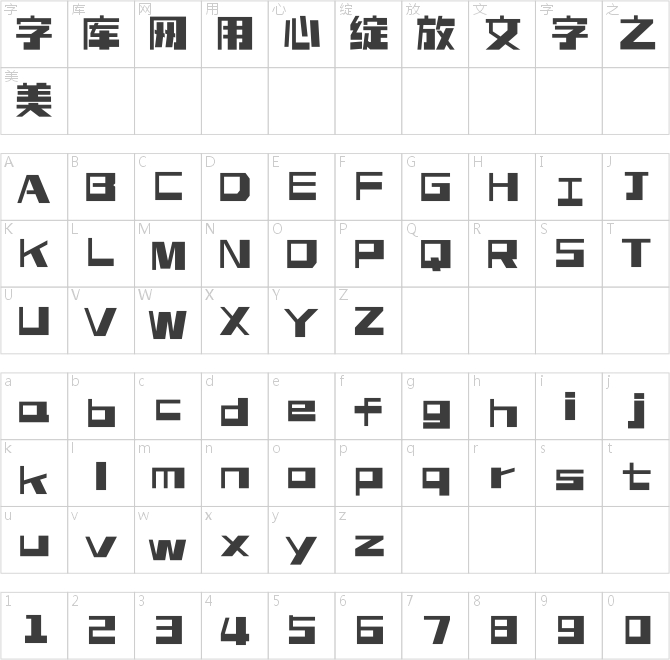
造字工房漢方體,字形設(shè)計(jì)中宮寬大,筆畫(huà)左細(xì)右粗,搭配巧妙,疏密得宜,留白均勻。風(fēng)格穩(wěn)重有力、工整硬朗,結(jié)構(gòu)醒目有力,引人注目,富有時(shí)代感,迎合了現(xiàn)代的審美觀。它適合用于標(biāo)題、廣告語(yǔ)、時(shí)尚刊物、名稱等主信息文字的設(shè)計(jì)。本字體為簡(jiǎn)體字庫(kù),采用OpenType/CID格式,Adobe-GB1-5編碼。基于中華人民共和國(guó)GB2312-80字符集標(biāo)準(zhǔn),另按需添加101個(gè)漢字。共收容字?jǐn)?shù)6864CJK漢字,ASCII常用字符100個(gè)。
造字工房漢方體字體字庫(kù)是一款讓人賞心悅目、百看不厭的中文字體,適合各類(lèi)廣告和產(chǎn)品包裝設(shè)計(jì)應(yīng)用,字體大小0.9MB,格式為otf字體,上傳用戶是釜源貿(mào)易,作者/版權(quán)方為造字工房